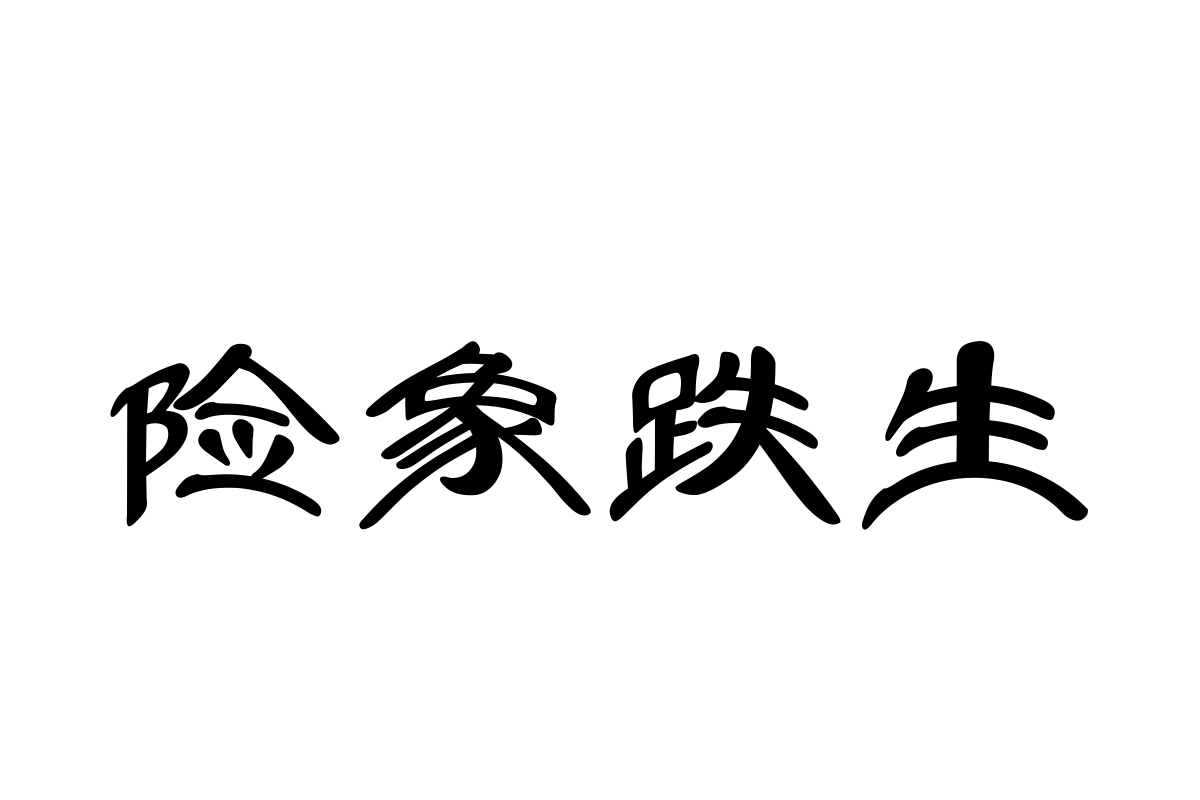
三极曲面简体字体是一款专为中文设计,具有独特美感和现代感的字体。它采用了简洁、流畅的线条,使得文字看起来既清晰又易于阅读。这种字体适合用于各种需要展示文字的场合,如广告、海报、网页等。
三极曲面简体字体的特点包括:
1. 简洁:该字体的笔画简单明了,没有过多的装饰元素,使得整体风格更加简约。
2. 现代感:通过使用现代化的设计元素,如斜体、曲线等,使得字体更具时尚感。
3. 可读性强:由于其独特的线条结构和合理的间距,使得文字在视觉上更易于识别和理解。
4. 适用性广:无论是在哪种类型的文本中,三极曲面简体字体都能展现出良好的视觉效果。
总之,三极曲面简体字体是一款非常适合现代设计的中文字体,适用于各种需要展示文字的场合。